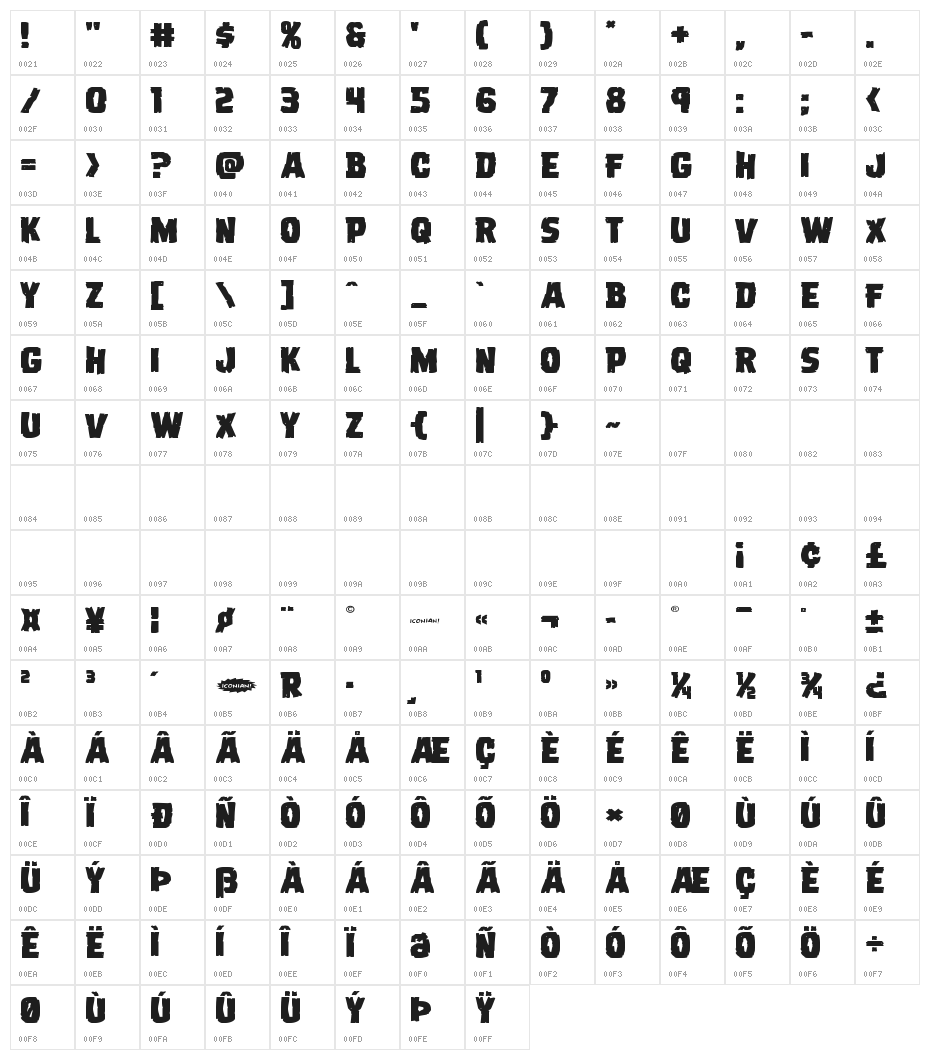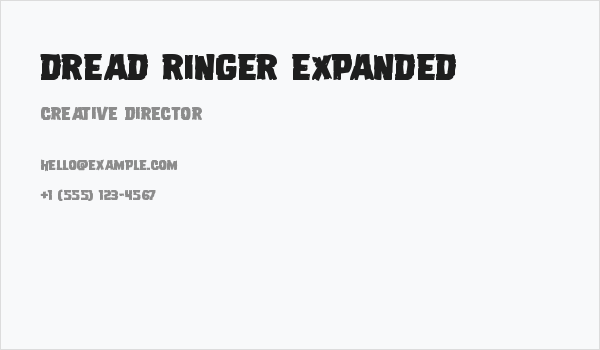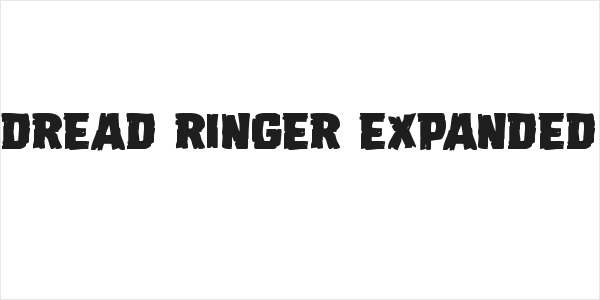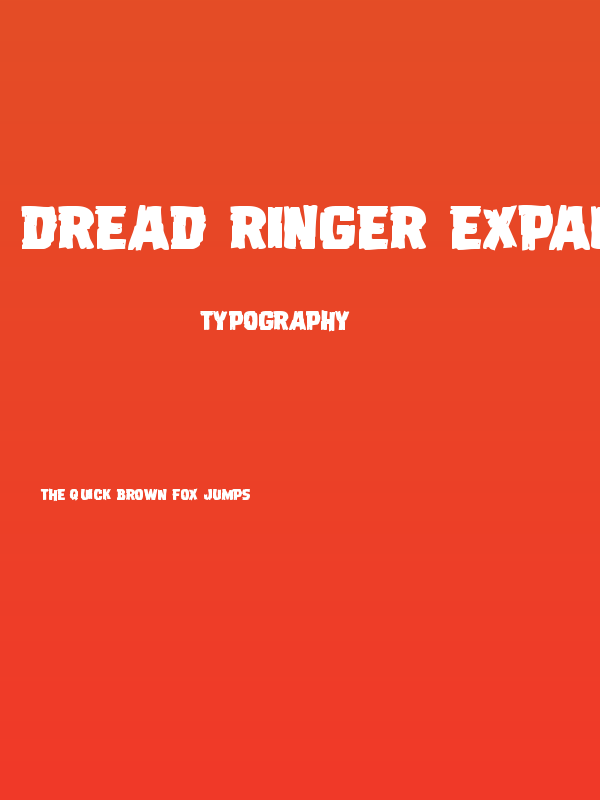
Dread Ringer Expanded Font
| Vorgeschlagene Projekte | Perfect for poster designs, album covers, video game titles, and branding that requires a bold, edgy aesthetic. |